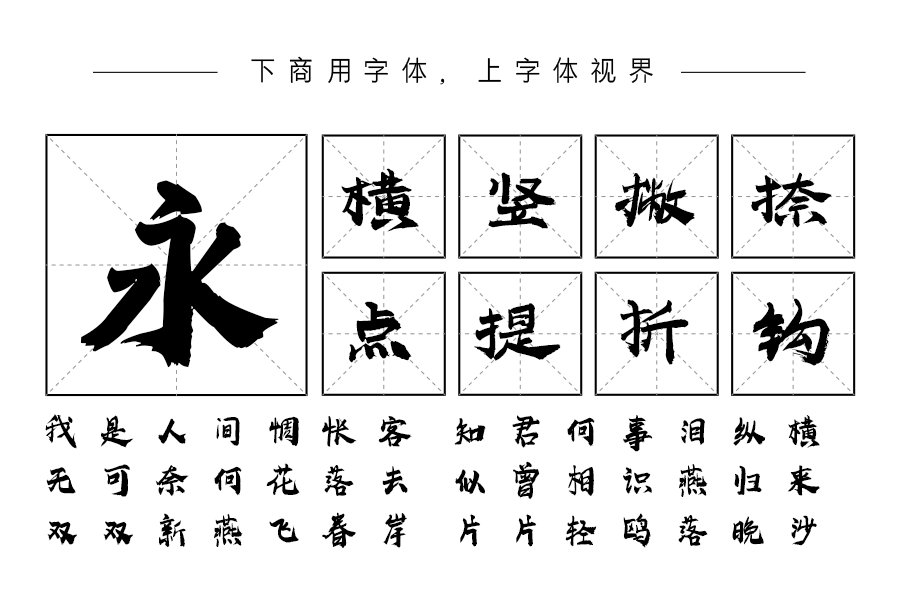
施申财字库系书法家施申财先生本人创作,自2018年开始便专心研究手写字体,独立完成字体版权申报达400余套(包括衍生),首创漆书微信表情10余款,系安徽省首批乡村文化带头人;安徽省文艺志愿者协会会员;六安市书法家协会副秘书长;舒城万佛书画院院长;山七镇文联副主席等,擅长漆书、隶书等字体。
今天给大家分享的是施申财字库的高清标题体:该字体是一款大气磅礴的毛笔飞白手写艺术字体,字体笔触粗实,书写端正大气。适合于艺术设计、平面宣传设计等应用。